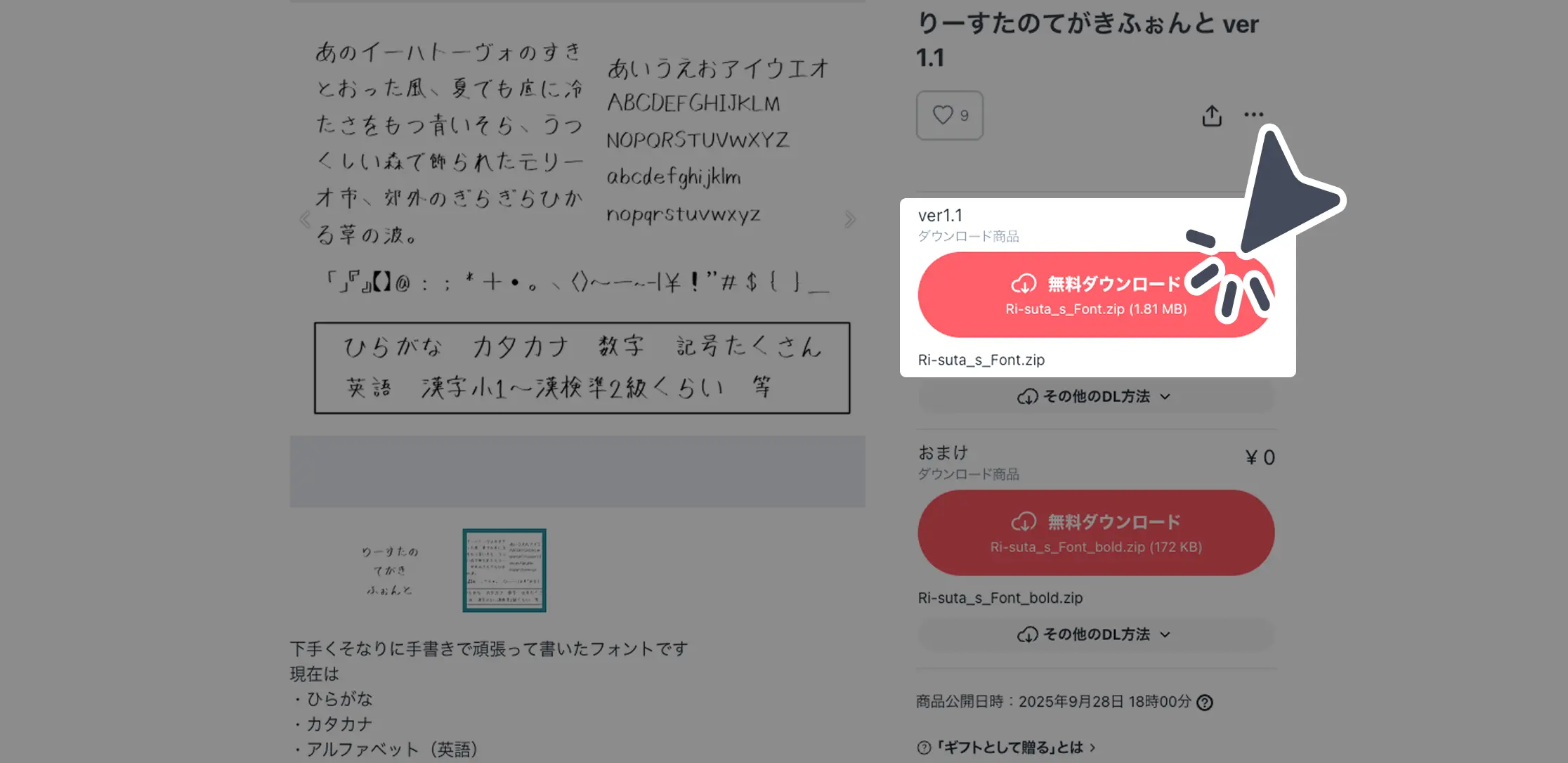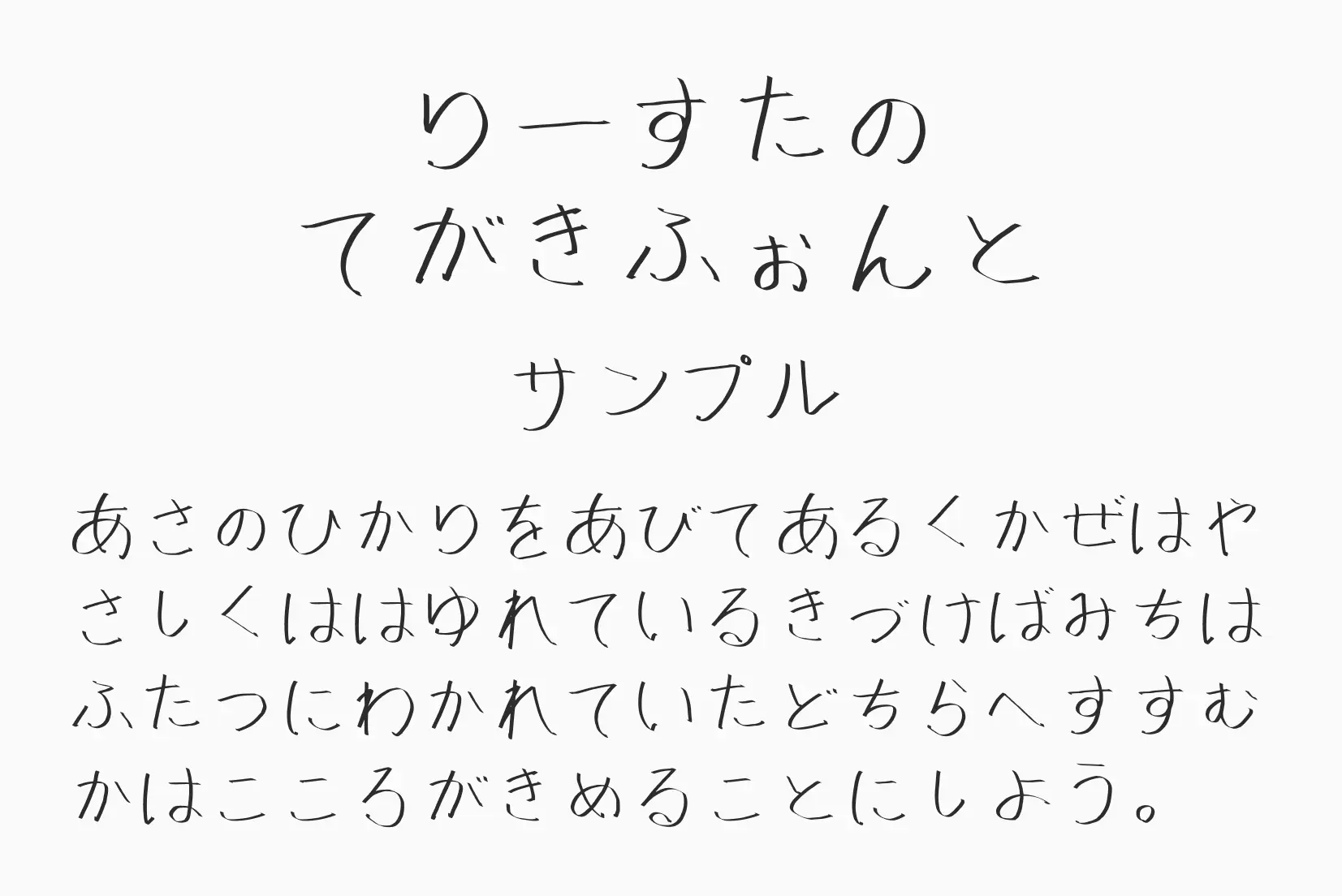
鉛筆でさらっと書いたような、素朴で等身大の手書き感が出るフォント。線のゆらぎがほどよく、硬すぎない“人の温度”を足したい場面に相性◎。メモ風デザイン、日記・手帳テイスト、SNS画像のひとこと、ショップの注意書きなどを自然にやわらげます。太字のおまけ版と組み合わせれば、見出し/本文のメリハリも作れます。
りーすたのてがきふぉんと
| 収録文字 | ひらがな・カタカナ・英字・数字・記号 |